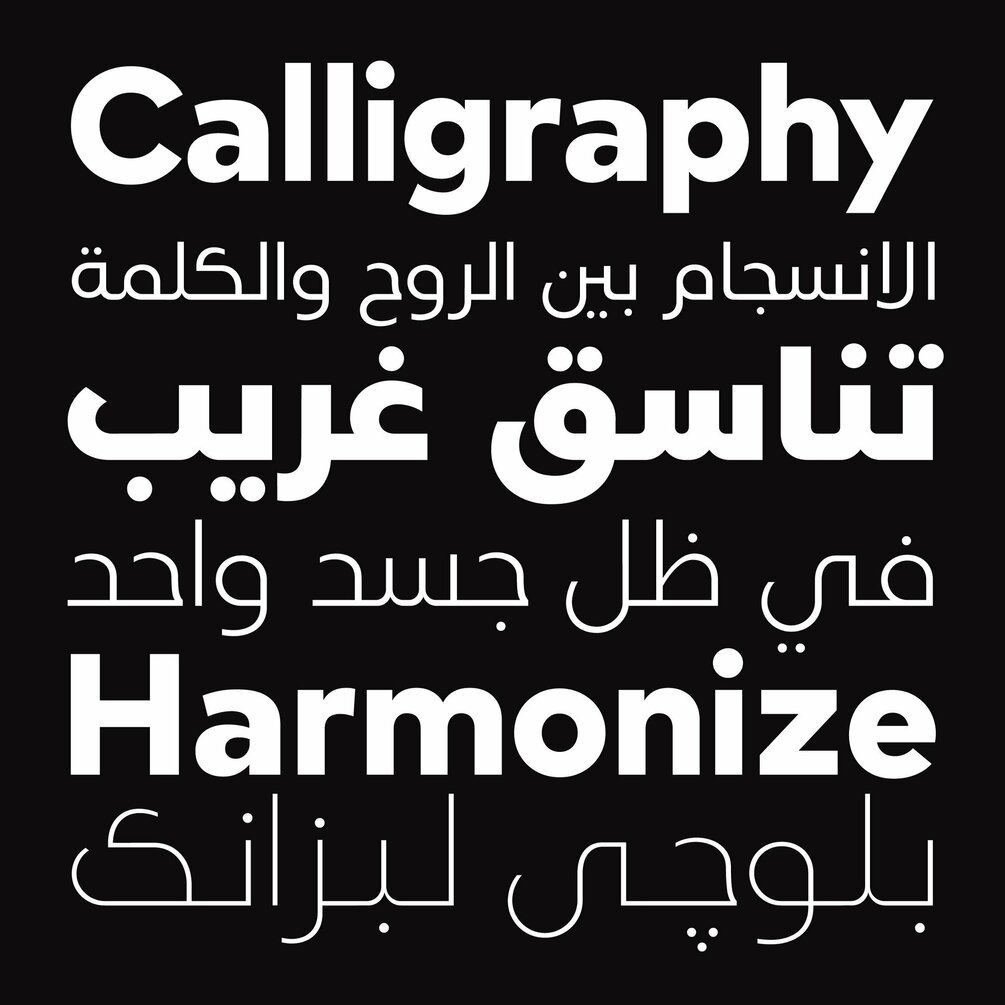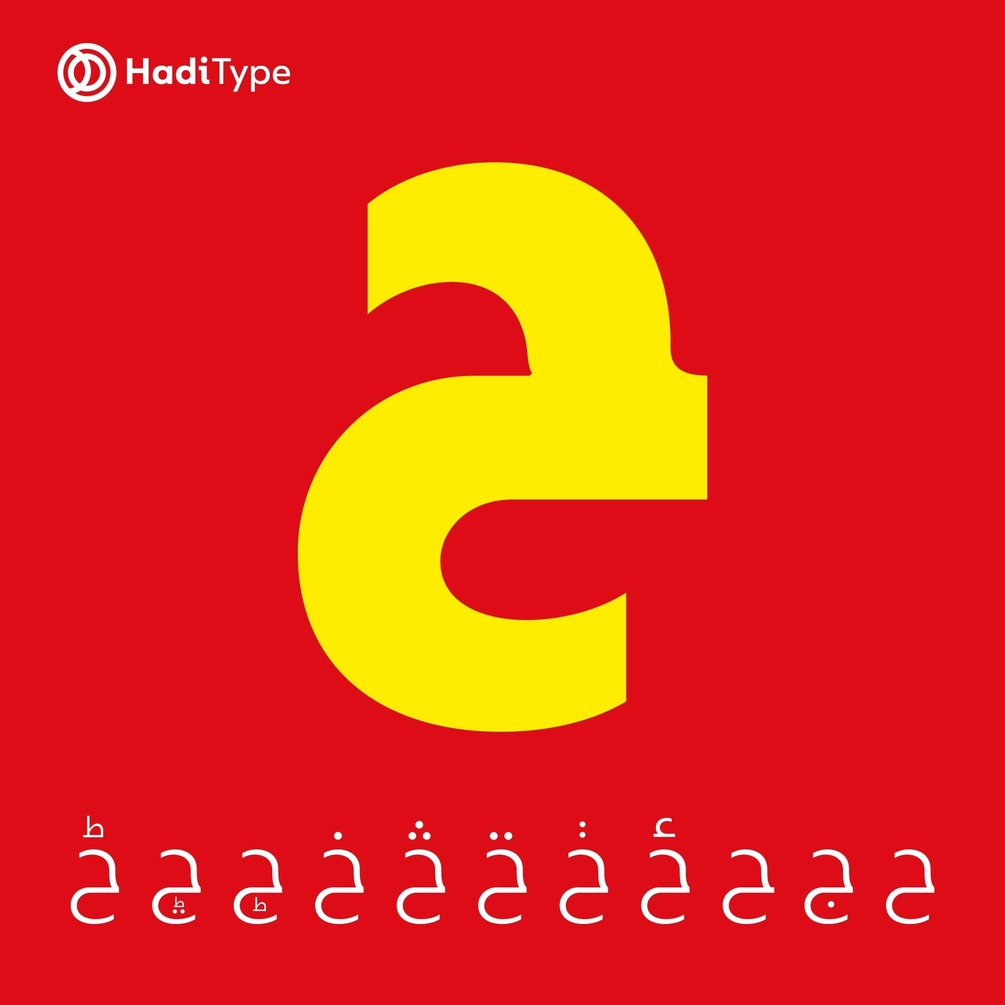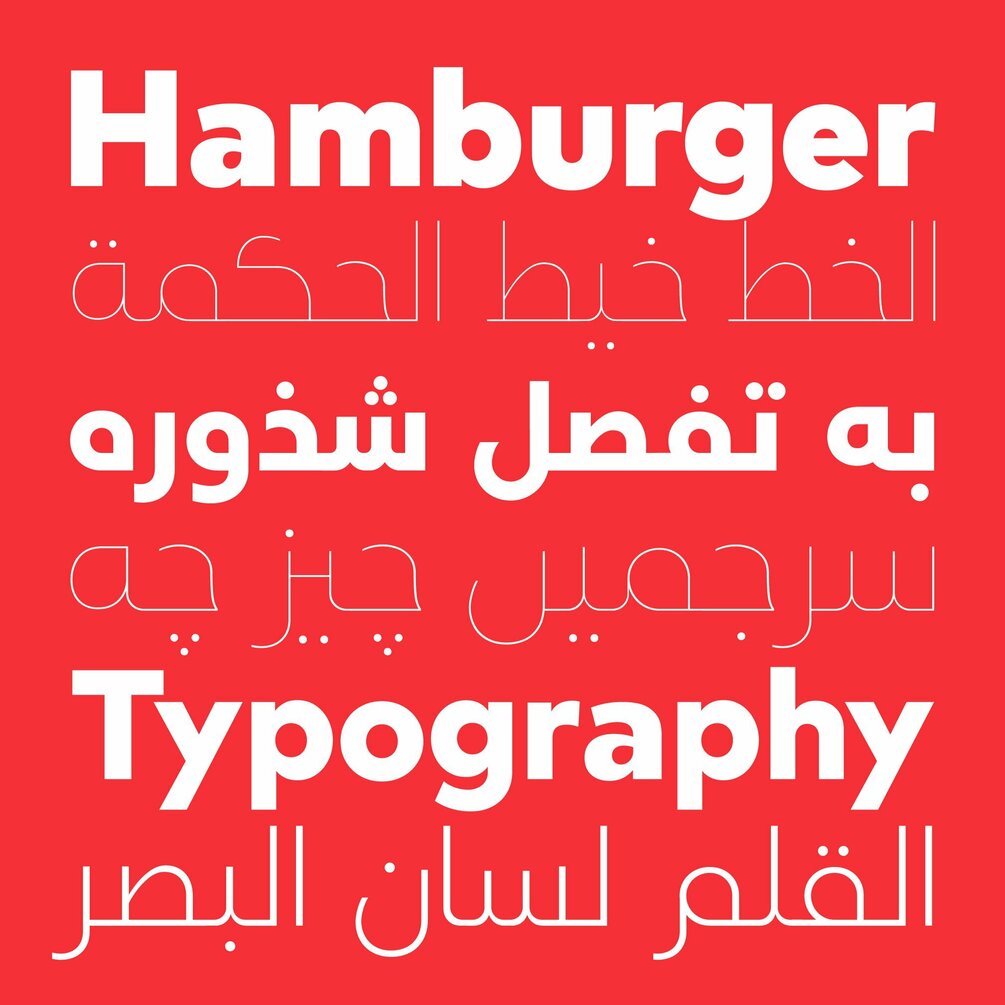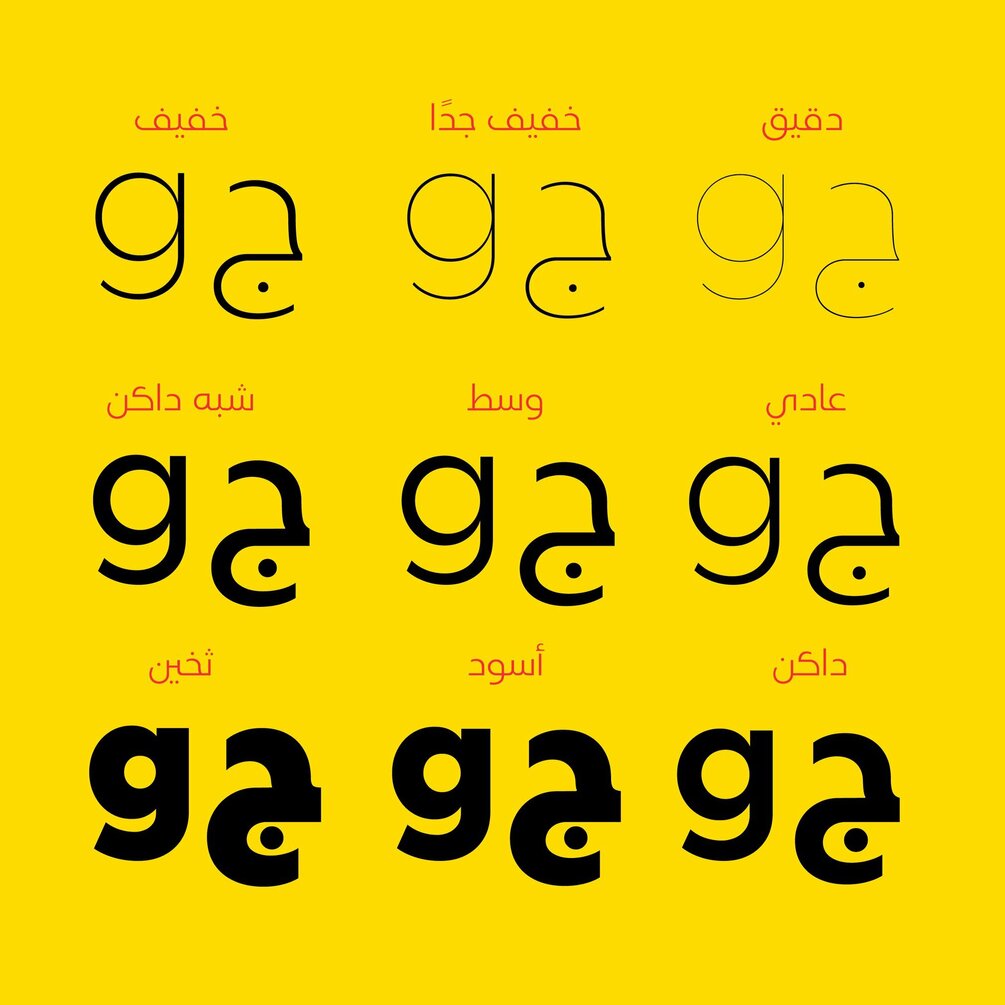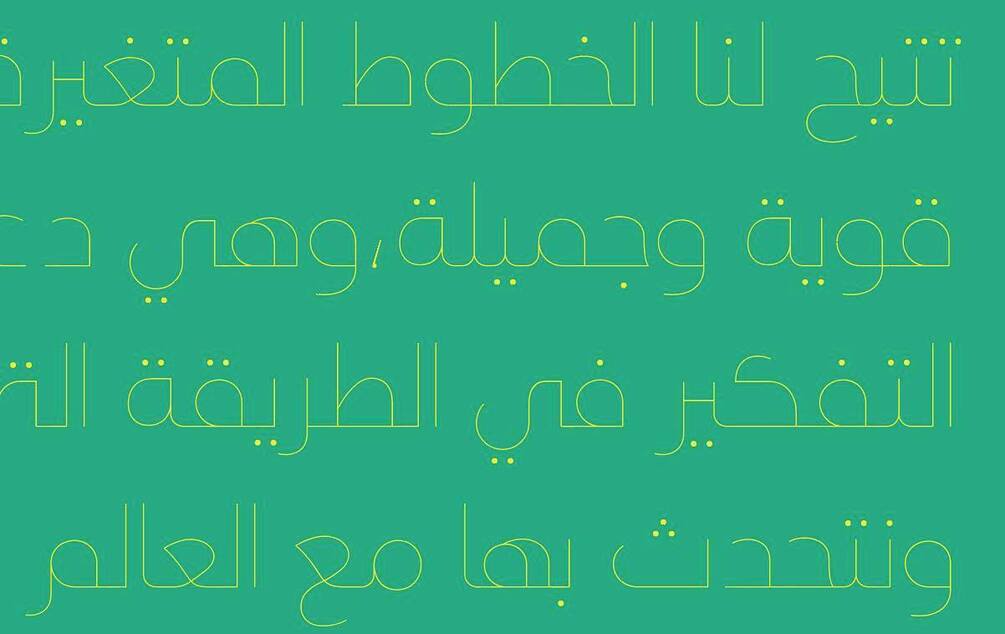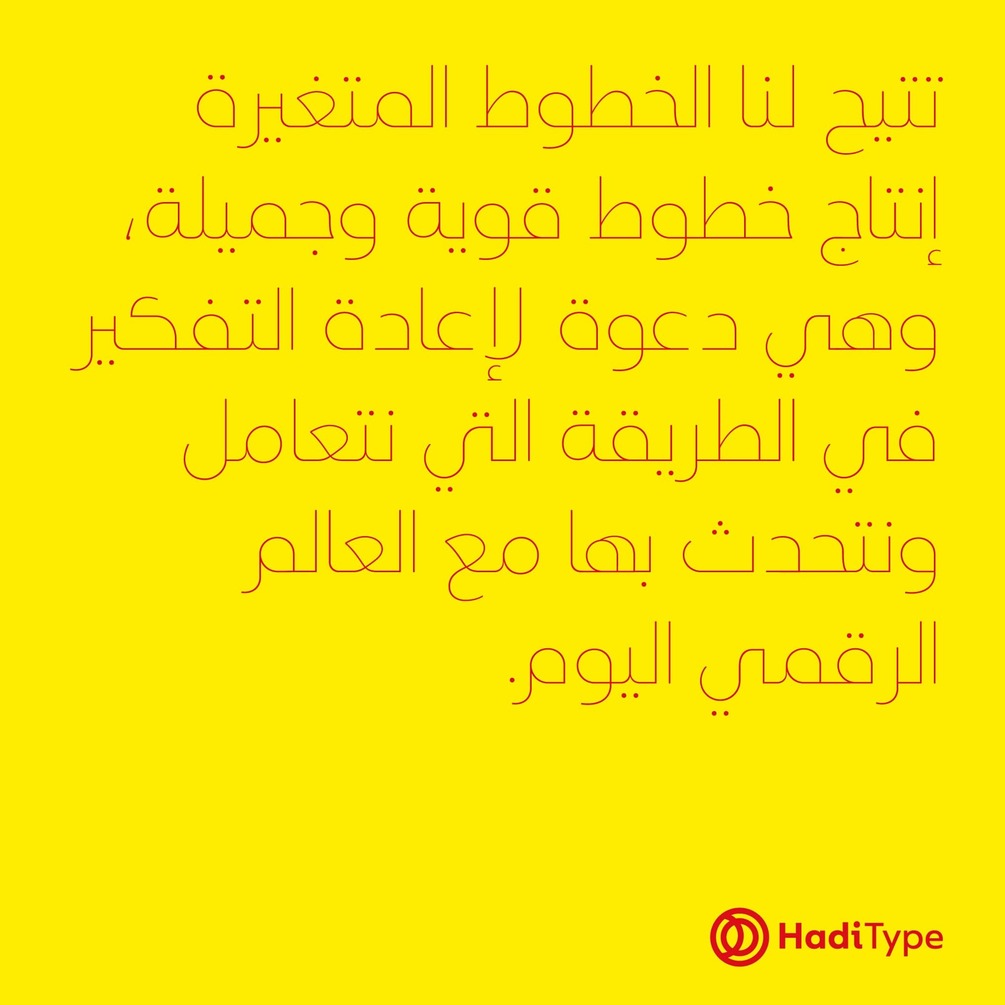
HT Qays Sans Pro - Complete Family
HT Qays is a contemporary geometric Arabic font, drawn and constructed carefully. Its structure is equal and visually controlled. Character forms are a combination of vertical straight lines that integrate visually with soft angles in some areas. This makes it a line of nature suitable for today's technological and visual development. The variations and weights of this font are suitable. To use companies in their names and appearance, and also suitable with the titles and logos and is also used in all the requirements of advertising and long texts, and short.
Based on the kufic calligraphy.
HT Qays supports Arabic, Persian and Urdu, a family of five weights ranging from light to Bold.
قيس هو حرف هندسي معاصر تم رسمه بعناية وحرصٍ شديدين، بنيته متساوية ومضبوطة بصريًا، أشكال الحروف هي مزيج بين الخطوط المستقيمة العمودية التي تندمج بصريًا مع الزوايا الناعمة في بعض المناطق فيه وهذا جعله خط ذو طبيعة تناسب التطور التكنولوجي والمرئي اليوم، تنويعات وأوزان هذا الخط مناسبة لاستخدام الشركات في أسمائها ومظهرها، ومناسبة أيضًا مع العناوين والشعارات كما إنه يُستخدم أيضًا في جميع متطلبات أعمال الدعاية والإعلان و النصوص الطويلة منها والقصيرة.
صمم قيس إعتمادًا على الخط الكوفي بنسبهِ الجلية الواضحة والقوية والواسعة لقراءة مريحة وعناوين متماسكة.
يدعم قيس اللغة العربية والفارسية والأردية، وهي عائلة مكونة من خمسة أوزان تتدرج من الخفيف وحتى السميك.